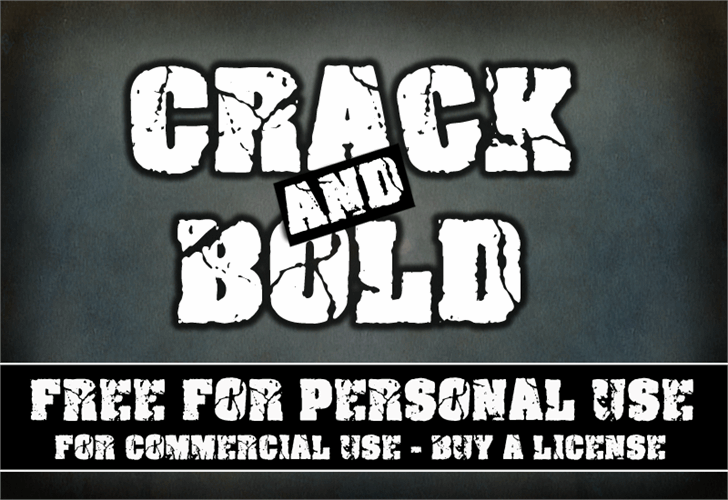
A fonte Crack and Bold é uma escolha perfeita para aqueles que buscam uma fonte forte e imponente para suas criações digitais. Inspirada nos estilos modernos de letra, esta fonte ‘display’ oferece um toque de destaque a qualquer projeto. Seu designer, Hamilton, tem apresentado um resultado profissional, combinando linhas elegantes com detalhes sutis que criam um efeito vibrante. Ideal para uso em design gráfico, publicidade e editoriais de mídia digital, esta fonte também é perfeita para criar identidades visuais memoráveis. Seu estilo chamativo certamente chama atenção nos materiais digitais onde você deseja transmitir uma mensagem forte e distintiva. Não importa o formato ou a plataforma, a Crack and Bold fornece uma maneira única de destacar seu trabalho. Seja para usar como fonte principal em um design gráfico ou criar um impacto impressionante através da publicidade digital, esta é a escolha ideal. Para usuários que buscam adquirir mais personalidades e características da fonte para uso comercial, Hamilton oferece licenças adicionais. Através de uma utilização gratuita à propósitos não lucrativos, mas com opções pagas para expandir seu arsenal de design, a font Crack and Bold é um investimento que vale cada centavo.